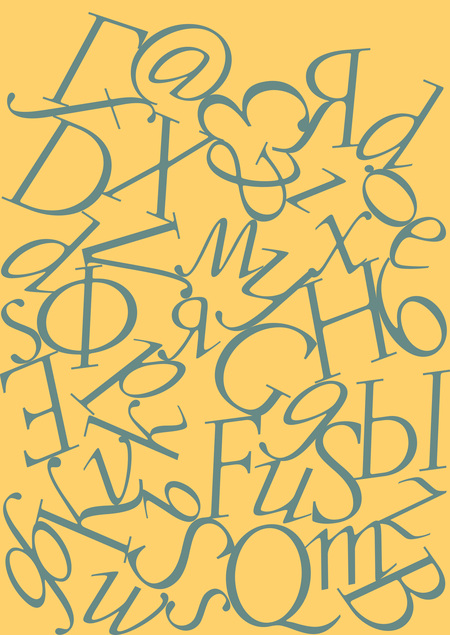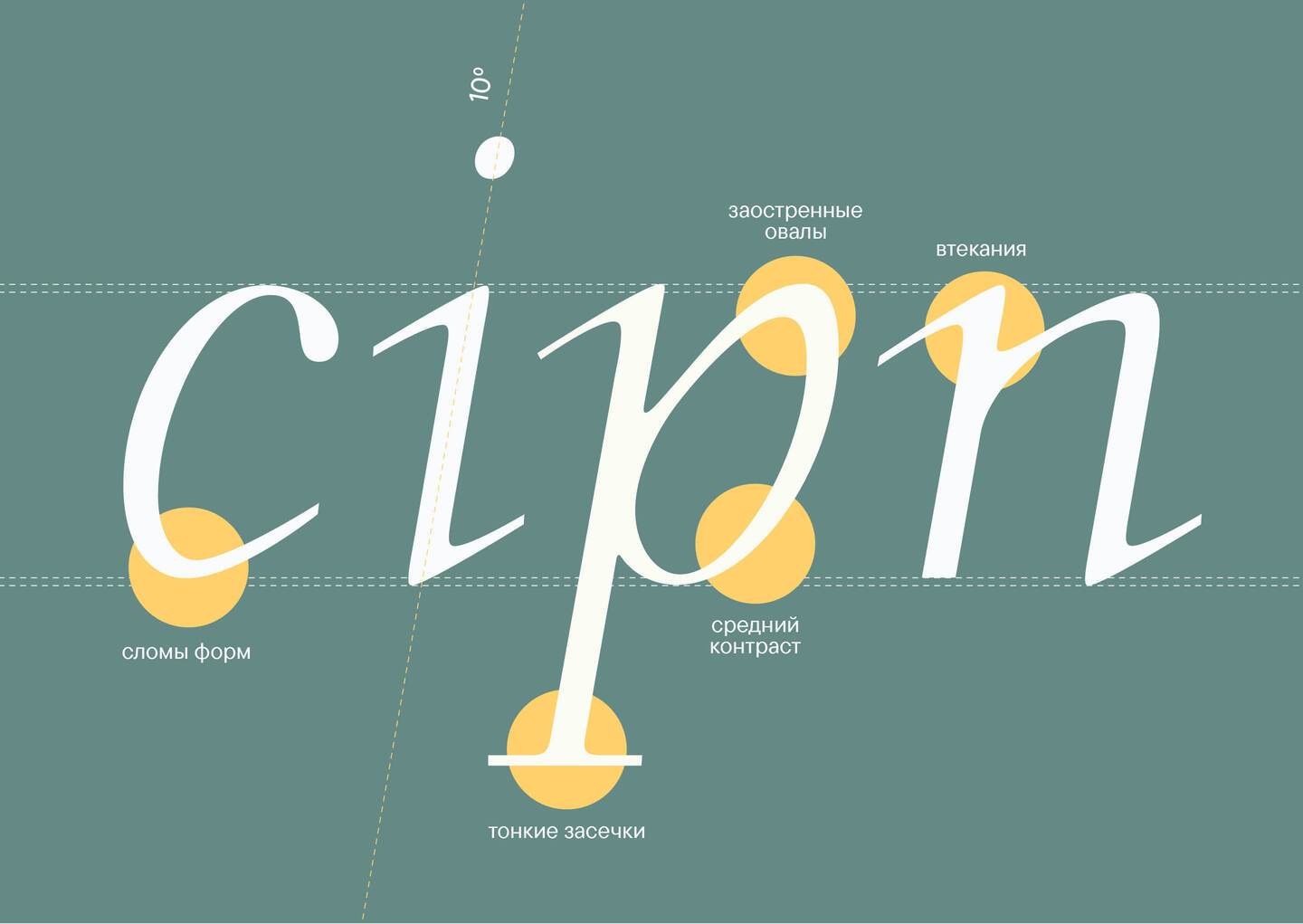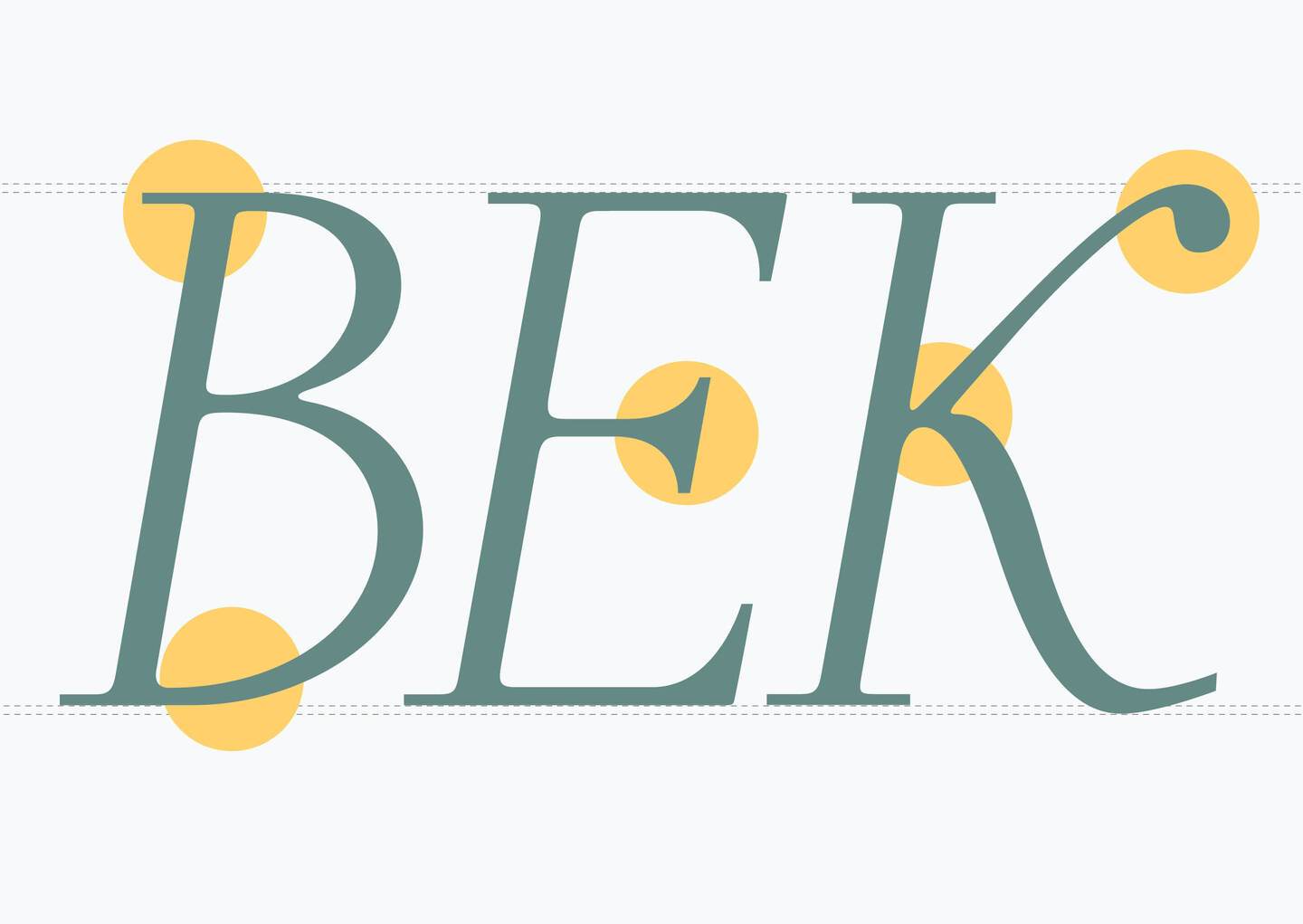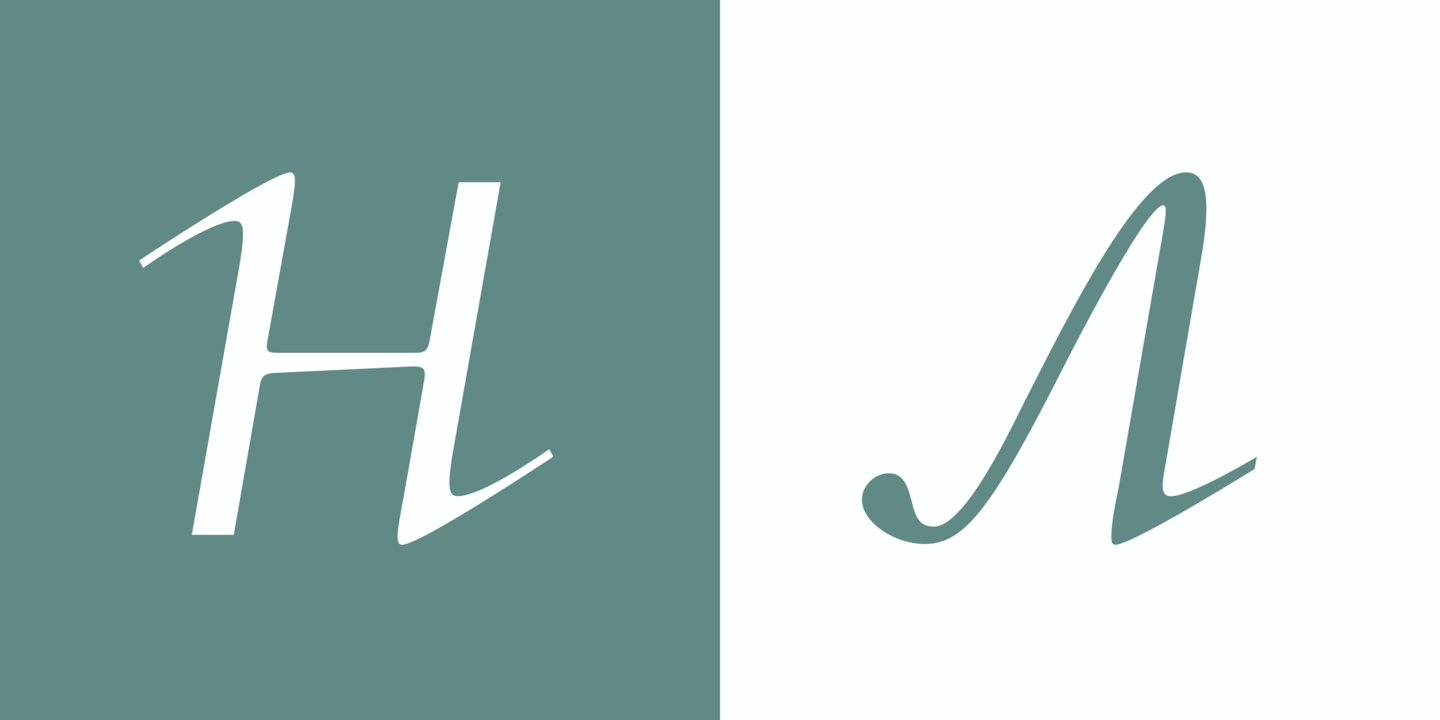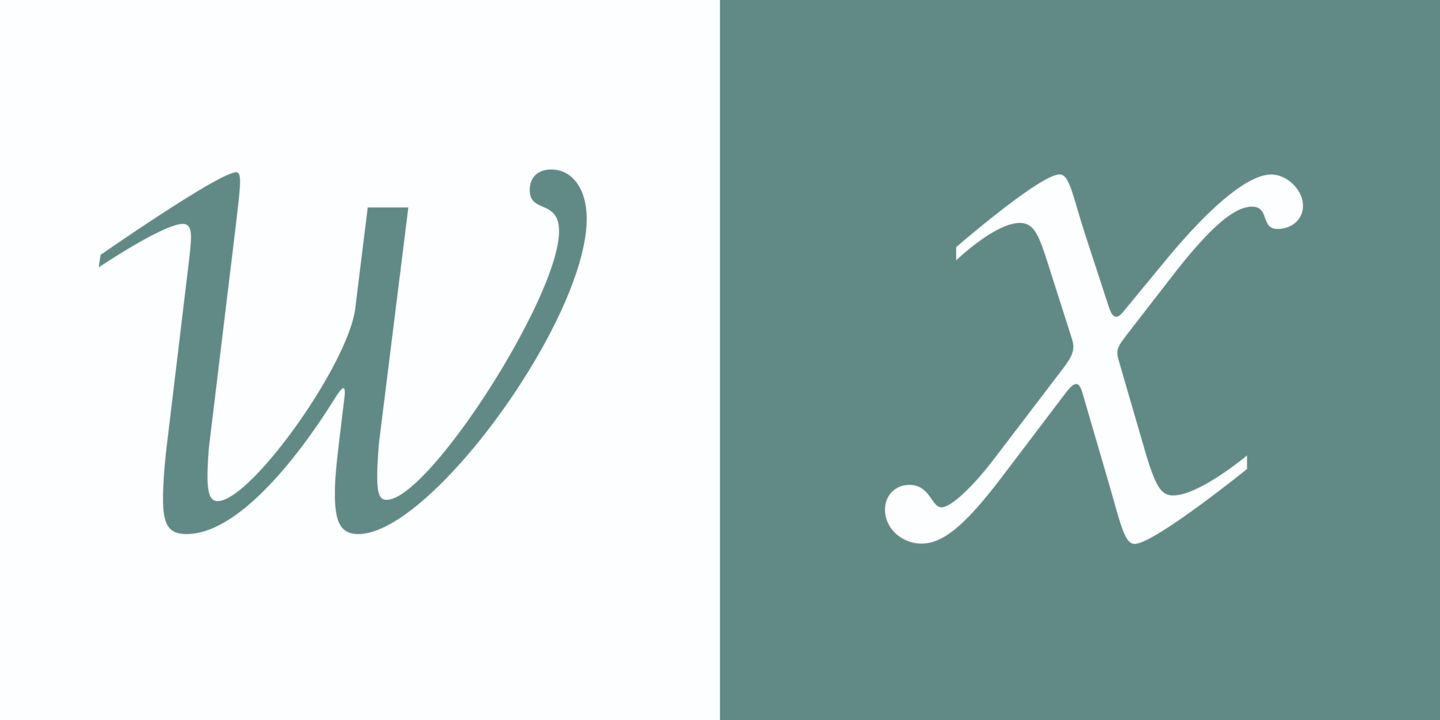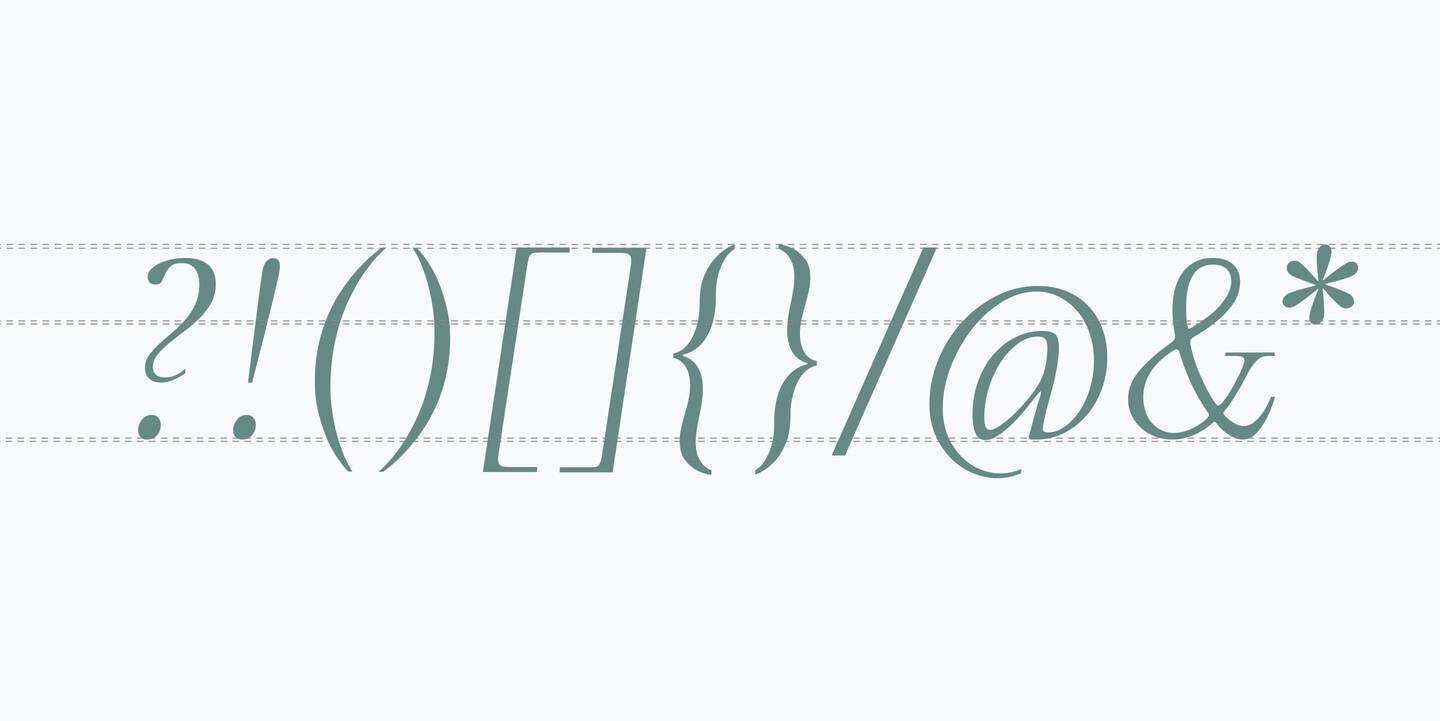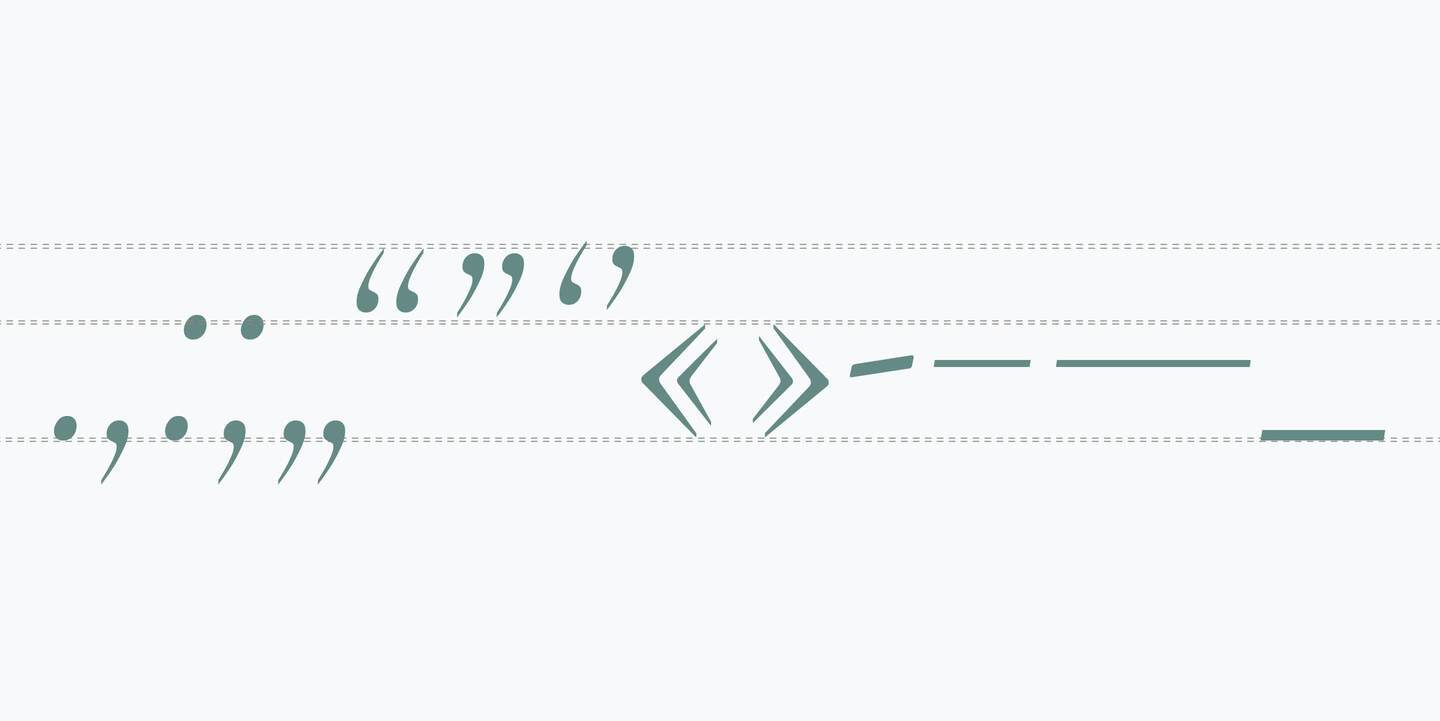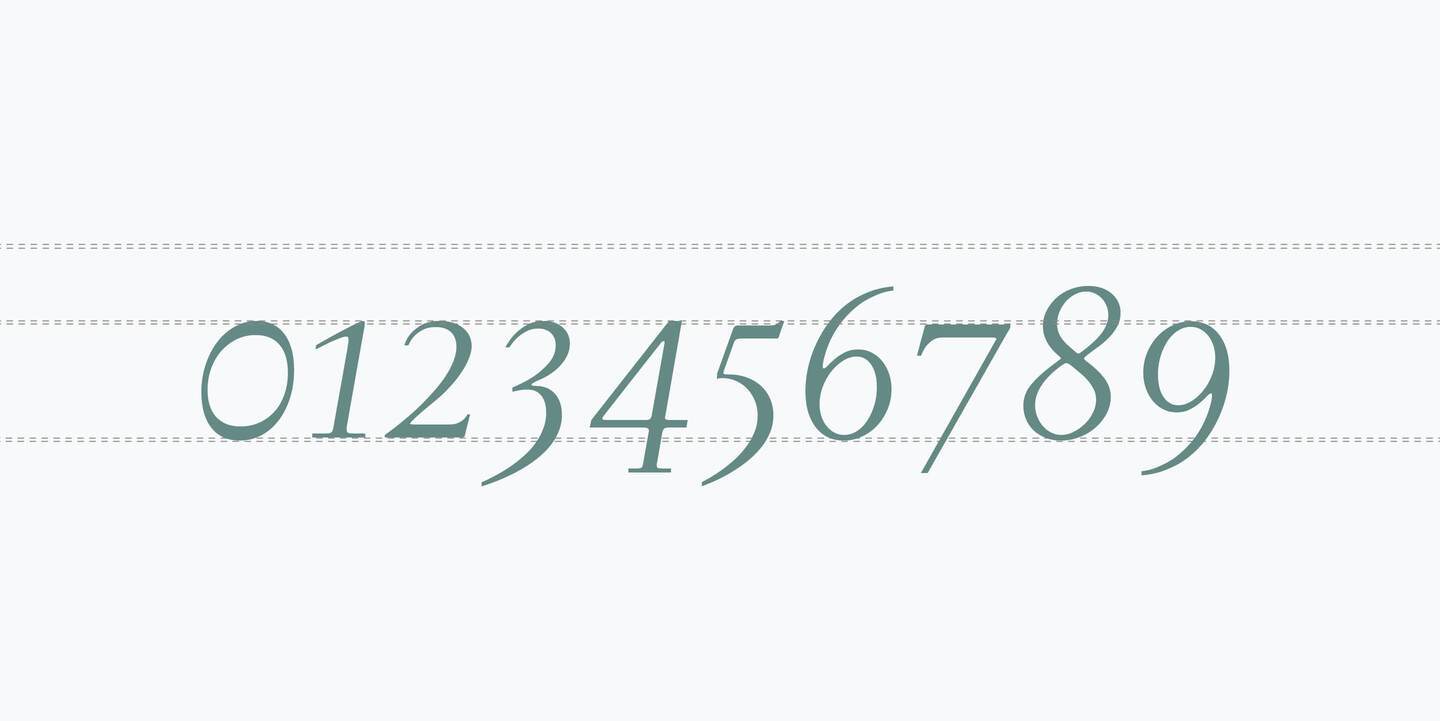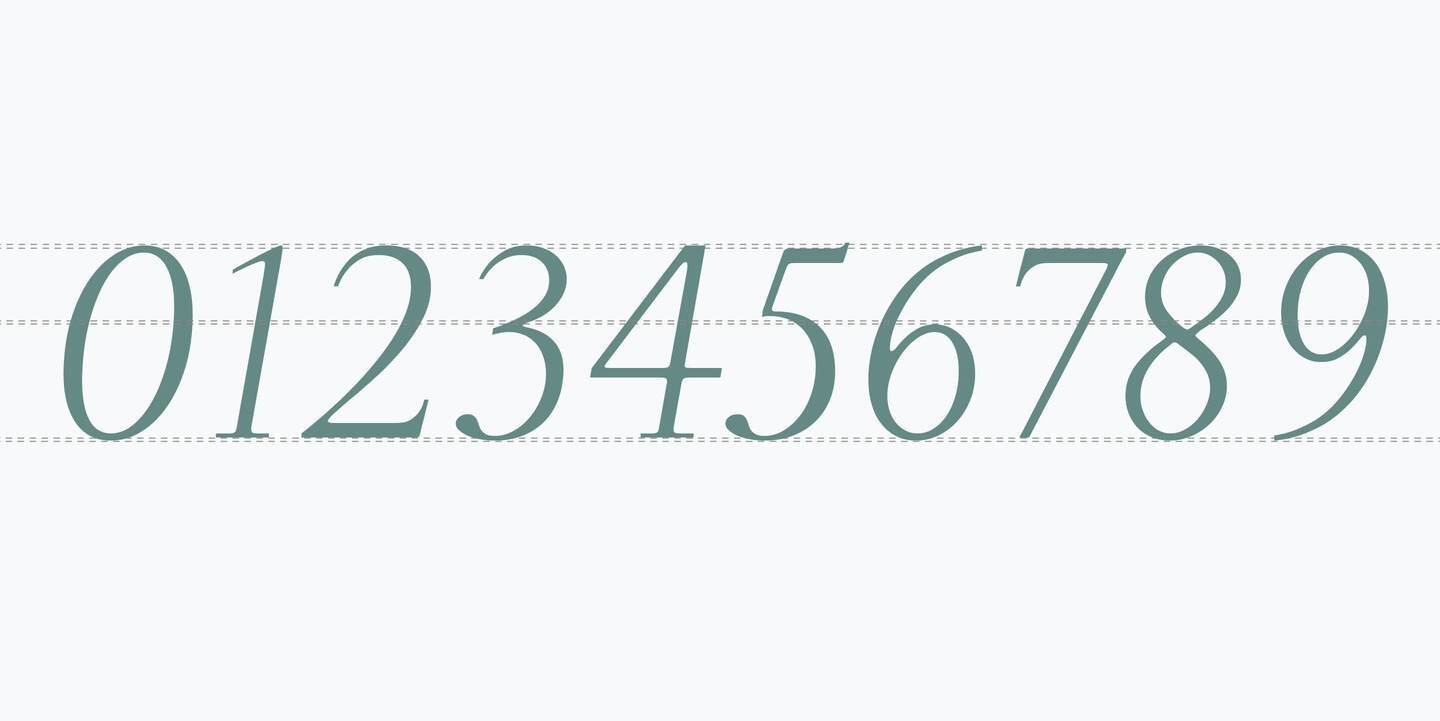
Halcyon font
Halcyon — типографский курсив, вдохновленный французскими курсивными шрифтами XVI‑XVII веков. Он обладает старостильной структурой с длинными, почти прямыми засечками в духе новостильной антиквы, изящными залипами и выраженным контрастом в толщинах засечек и дополнительных штрихов.
особенности шрифта
русский алфавит
английский алфавит
маюскульные, минускульные цифры и символы
знаковый состав